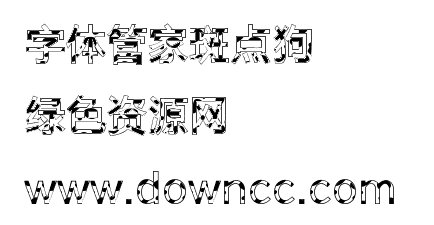
字體管家斑點(diǎn)狗是一款空心字體,同時在文字中增加不同的黑點(diǎn),狀死“斑點(diǎn)狗”而命名,讓文字更顯得十分醒目而可愛,快來綠色資源網(wǎng)體驗(yàn)吧!
字體管家斑點(diǎn)狗以黑體字體為原形,在字體內(nèi)加入斑點(diǎn)圖案,整體結(jié)構(gòu)端正大方,識別性強(qiáng),同時字庫完整,適用范圍較廣,能滿足用戶日常工作的需求!
斑點(diǎn)狗字體出自字體管家,有著十分時尚顯眼的外觀,讓文字經(jīng)過處理過更加吸引讀者的目光,造型大方而精簡,鏤空的造型也很能贏得大家的好感,可以運(yùn)用在平面設(shè)計(jì)、藝術(shù)設(shè)計(jì)、包裝設(shè)計(jì)等諸多場合!